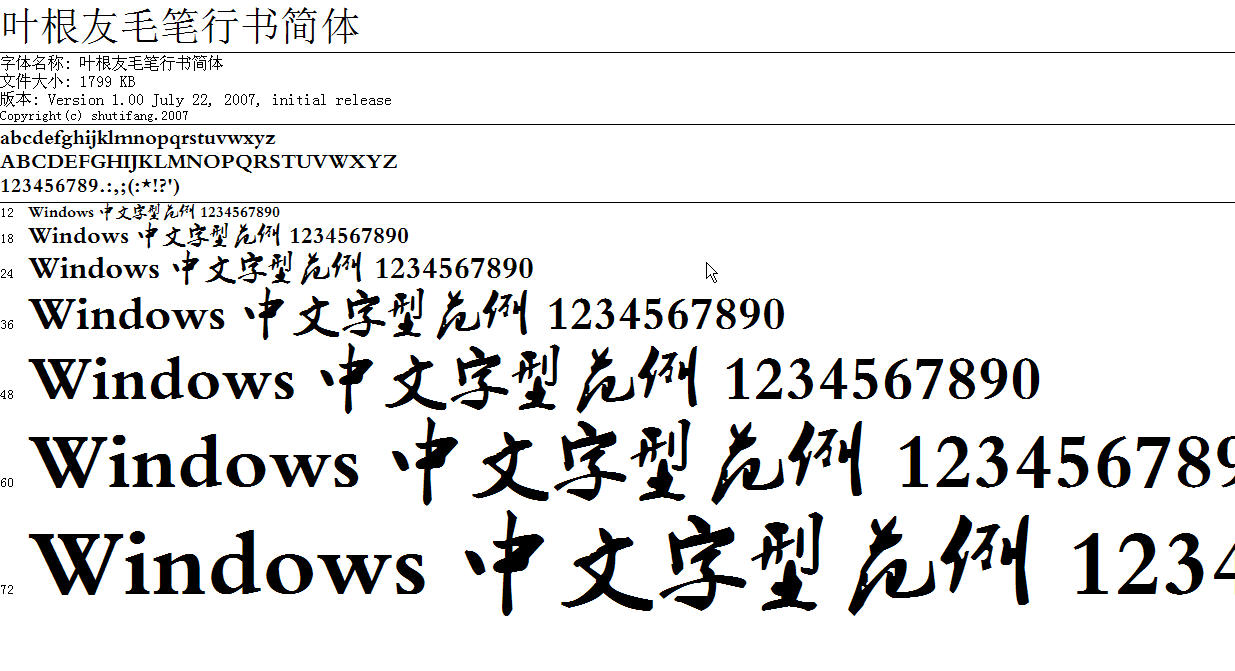
yegenyoufont是什么字體?yegenyoufont字體就是葉根友字體,結(jié)構(gòu)簡省,線條灑脫,筆畫有粗有細(xì),特點(diǎn)鮮明,字型效果非常棒,感興趣的朋友快來下載吧!
葉根友的書法有著與眾不同的風(fēng)格體現(xiàn),其行草書法是屬于主要的書法表現(xiàn)形式,在取他之長、補(bǔ)己之短的精神努力追求下,取得許多葉根友書法愛好者的一致認(rèn)同。葉根友說,書法藝術(shù)講究的是不變中求變,行筆過程快中有慢,慢中有勁,動(dòng)靜結(jié)合、快慢相融、做到章法錯(cuò)落有致,書法布局空間的形式美等的書法創(chuàng)作理念。